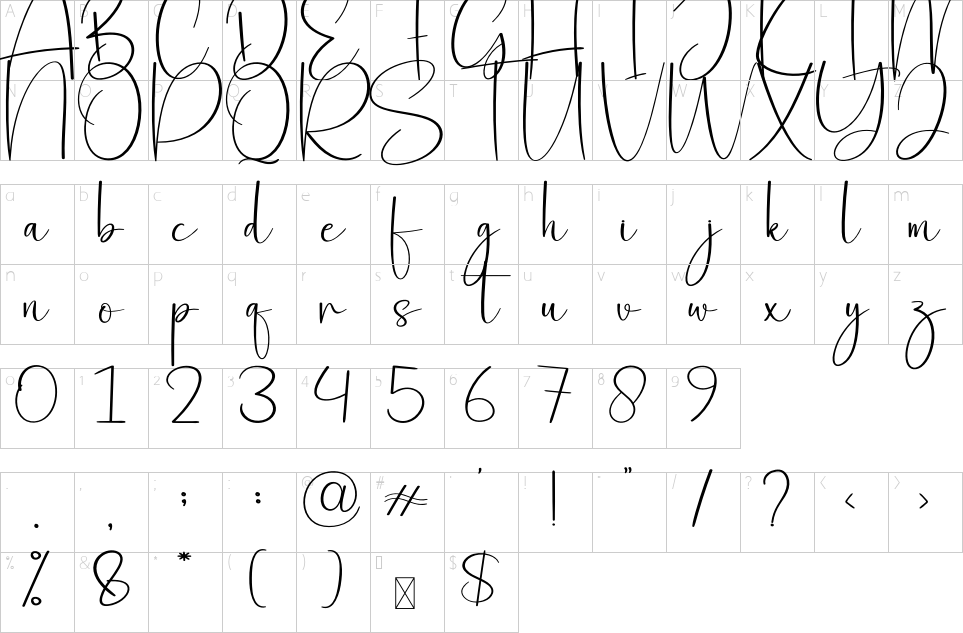
A Satnight Font oferece um estilo clean e contemporâneo para personalizar seus projetos de escrita digital. Desenvolvida por William Jhordy, esta fonte está disponível tanto para computadores Windows quanto Mac. Com seu design leve e elegante, a Satnight é perfeita para aplicativos de design gráfico, sites e até mesmo para a publicação de conteúdo online. Desfrute do conforto e da praticidade dessa fonte gratuita, que já foi baixada mais de 550 vezes. Experimente-a hoje e revolucione sua maneira de usar letras digitais.